第二部分:**违反“规则”绘图
好处:赋予自己绘制困难形状的能力。
矢量绘图的技巧在于如何最轻松地实现困难的形状。
但怎么做呢?
首先,我们来分解不同类型的矢量规则。
三种类型的矢量指南:
- 导出字体的矢量指南(初学者)
- 插值的矢量指南(制作字体家族)
- 绘图的矢量指南(中级)
**注意:**如果你是初学者,请先看看这里的规则。
不要使用导出规则绘图: 许多优秀的字体设计师会违反规则来绘制他们的作品。
#1 把手向前推曲线 而不是“节点在极点” 上下绘制更容易。 但上下的东西通常更无聊。 “节点在极点”是一种静态方法。 它专注于静止点——节点。
如果你有一个静态字体(我有很多),考虑极点是很好的。
静态字母感觉坚固。它们的压力轴是0°。
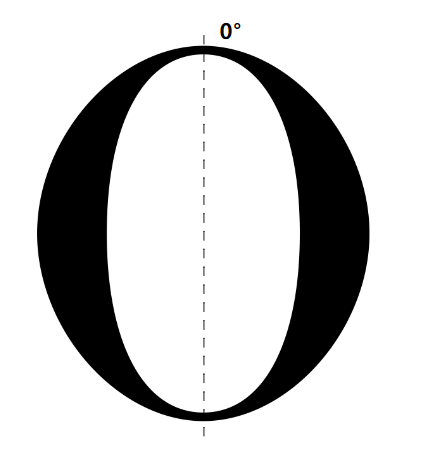
这里有一个更紧张的静态形状的例子,因为曲线张力很高。
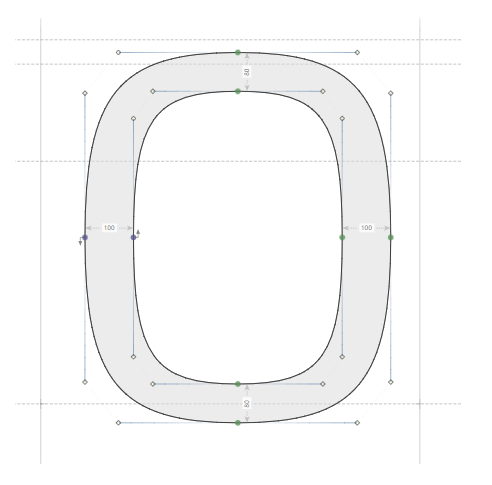
这里有一个动态形状的例子。
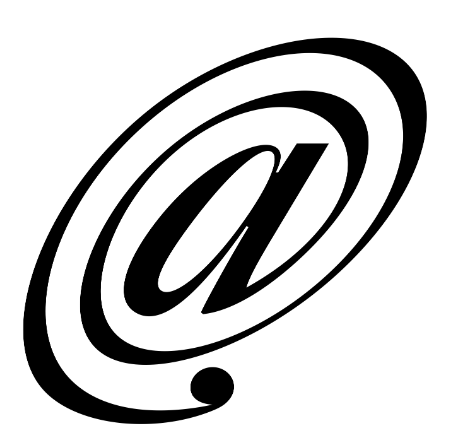
我将稍后展示节点结构。
这种类型的形状很难用垂直和水平节点制作。
原因如下。
重新思考把手的方式:
让我们回到基础。
把手力量 把手(黄色钻石)像这样推出曲线。
但这并不是全部。
如果我们把一个把手设为零,它就不会施加任何向外的力量呢?
你可以通过按住ShiftAlt,然后点击一个把手来使把手为零。
这里有一个把手为零,“缩回”的例子。
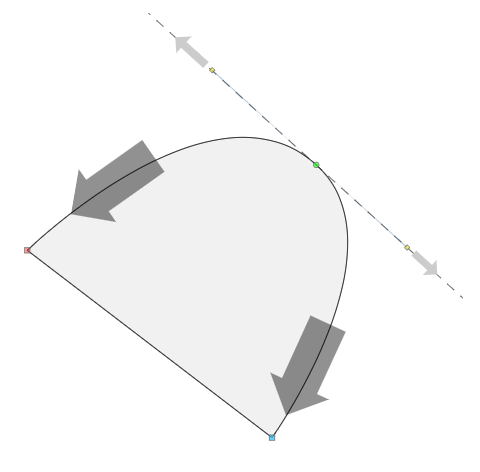
蓝色和红色的节点的把手是零。
它们不施加任何向外的力量。 但它们有向内的力量。
节点就像黑洞一样吸引曲线。
节点力量,即向内吸力,比把手的推力更强。
无论你把把手推出多远,节点总会吸引曲线。 你可能认为这是“把手力量”和“节点力量”。弱力和强力。
所有力量一起:
好的,现在我们将把零把手拉出来。(使用Alt-拖动将它们拉出来。)
这是这个片段中的所有力量。
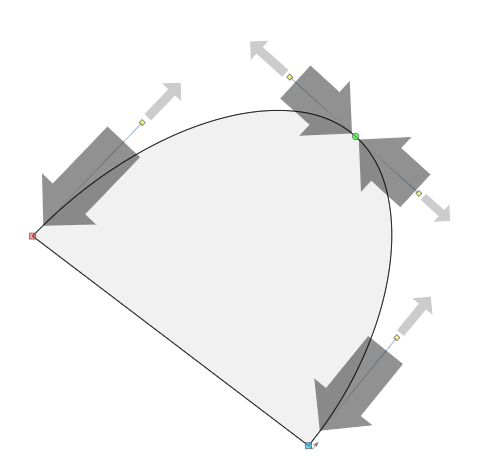
现在红色和蓝色节点有了把手,强力量就沿着这些把手的方向。 这意味着,弱力和强力都沿着把手移动。
警告: 关于缩回的把手:缩回的把手更容易处理,因为如你所见,涉及的力量更少。然而,缩回的把手转换为TT曲线时效果不佳。你会得到糟糕的折痕。
正是这些力量的相互作用,推出和吸入,让你能够操纵曲线。
除此之外,你还有其他工具来操纵你的曲线。
把手方向: 把手还指定方向。
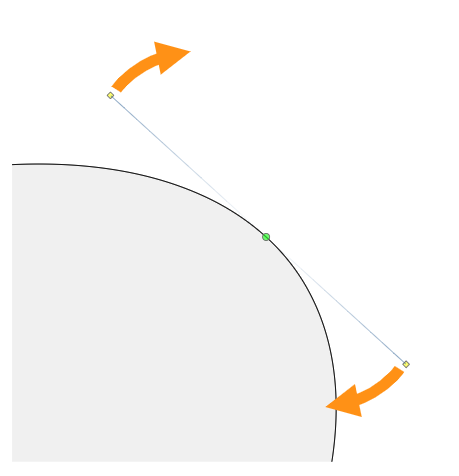
当你改变把手角度时,它会改变曲线的推出方式。
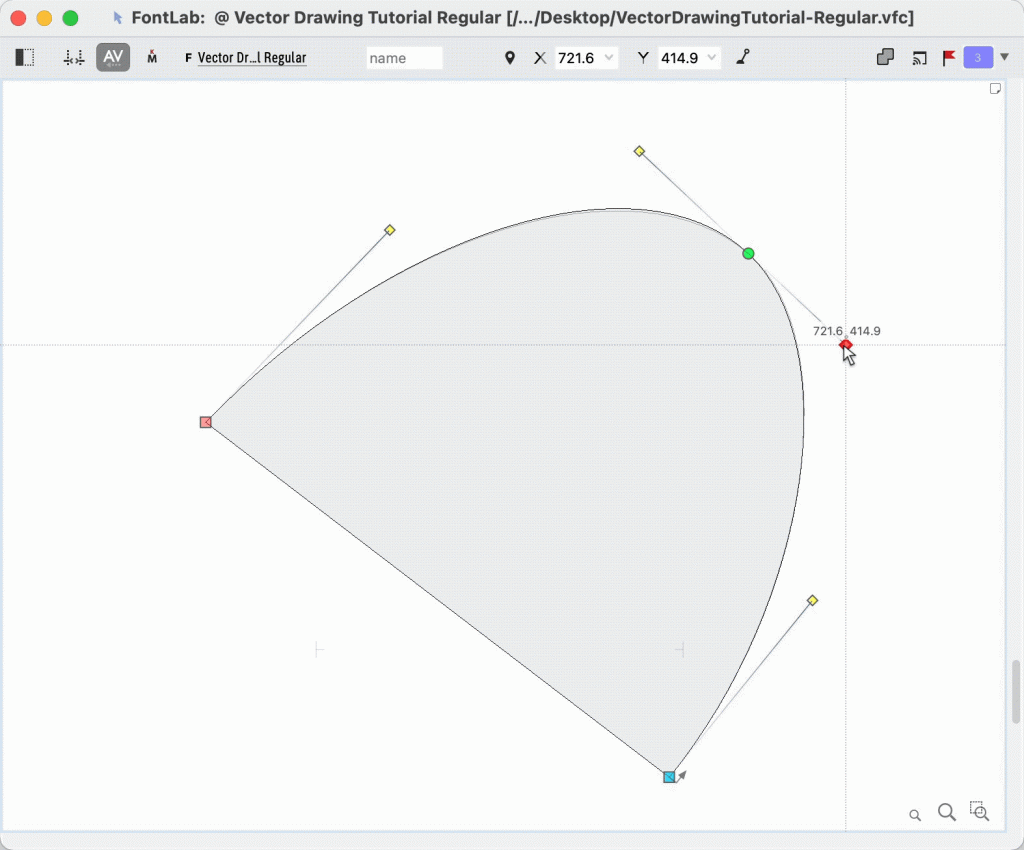
所以现在……极点节点的问题是什么? 你无法控制方向!把手角度必须保持固定!
将力量和把手方向结合起来: 所以不要只考虑节点位置。 如果你想制作动态形状,考虑把手。它们推动你的曲线向前。
这是带有节点结构的漩涡形的@,注意把手是如何推动漩涡前进的。
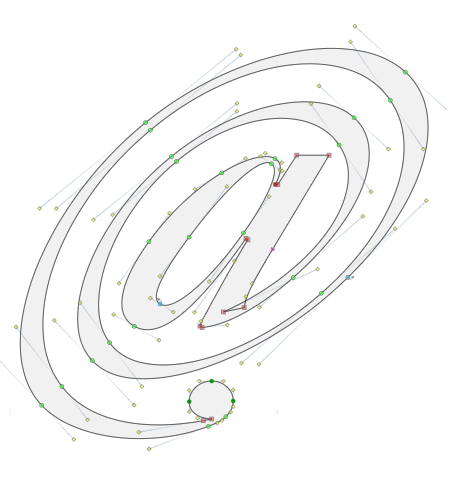
这是压力轴。
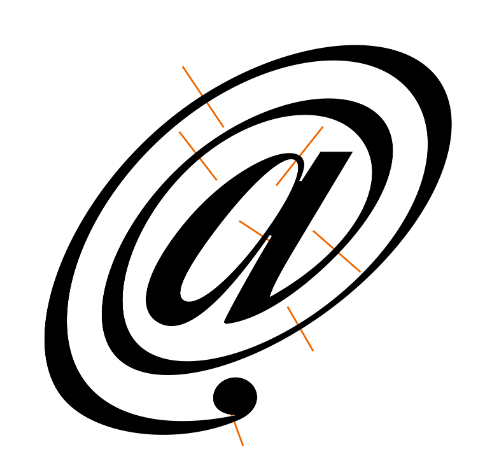
看看把手并不总是平行的。当内曲线需要与外曲线不同地改变时,用微妙的方向变化来做这个更容易。 用“节点在极点”,把手保持水平或垂直。方向变化是不可能的。
提示: 按住Cmd拖动以改变把手角度。调整应该是非常轻微的。
信息: 在绘图时遵循“浅曲线上无节点”的规则。
警告: 记住,这是你绘图的方式,但不是导出的方式。这是变化的错误节点结构。
专业提示: 这次讨论有点过于简化了。很多时候我会使用极点节点把东西放在正确的位置。然后我会增加斜向的节点。然后删除极点的节点。
#2 无折痕 这可能是你不应该打破的规则。
#3 额外节点,稀疏节点 而不是“简洁路径” 当你绘图时,有时你想要有额外的节点。在细化阶段,你总是可以去掉这些。 更多的节点=更多的把手=更多的控制=更微妙的曲线=更多的工作 更多的把手可以让你实现一些非常好的形状。
另一方面,有时拥有较少的节点也有帮助。 较少的节点=较少的把手=较少的控制=基本曲线=较少的工作 较少的把手特别适合数字2、3和5。
除了单独移动节点,这里还有一些其他事情你可以做。 你可以使用Tunni线来精确改变把手的“力量”。 拖动段。(确保段没有被突出显示。) 你可以看到把手的跷跷板。 按住Alt并拖动,你可以一起移动把手。
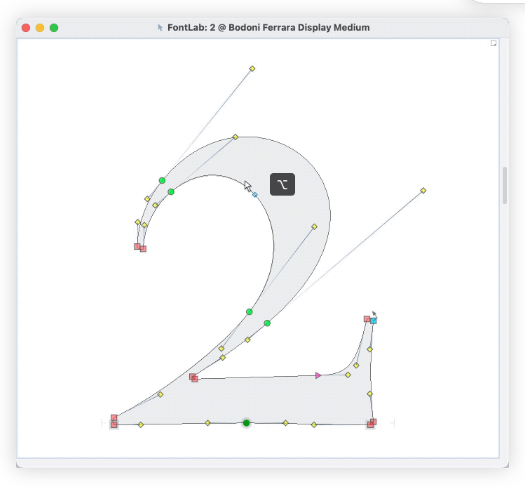
#4 暂时忽略魔法三角形 而不是“魔法三角形” 你可以暂时忽略魔法三角形来调整节点。上面两个例子忽略了三角形规则。 有时这样做更容易。 但大多数时候你想要使用三角形。
#5 任何路径都行 而不是“路径方向” 假设你的b设计是d的反向。
好吧,如果你做一个元素并反转d,它看起来像这样。
这种错误路径方向是可以的。如果你决定修改d,它可以帮助你节省时间。 路径方向在导出时会被修正。
#6 使用重叠 而不是“避免重叠” 重叠被广泛使用以获得良好的插值。 但此外,它们也可以使像对角线字母这样的东西更容易管理。(因为你可以独立移动侧面。) 避免双重重叠 你仍然需要避免双重重叠,因为那些会产生白点。 查看有关字母配置和可变字体的教程,以获取更多信息。
为导出做准备: 一旦你完成了绘图,你确实需要为导出做好准备。你需要极点的节点,以及所有那些好东西。 你的图形越静态,你就越可以使用导出规则来绘制。这可以在后期制作中节省你的时间。